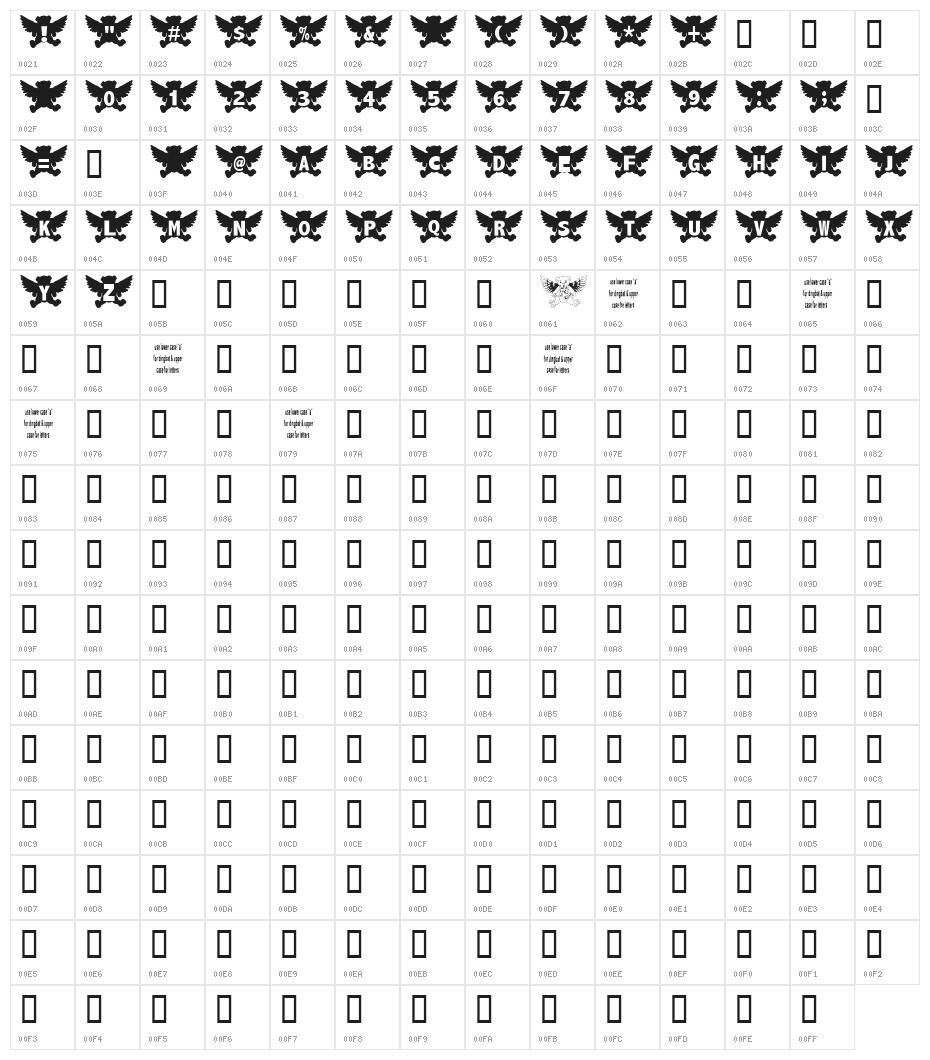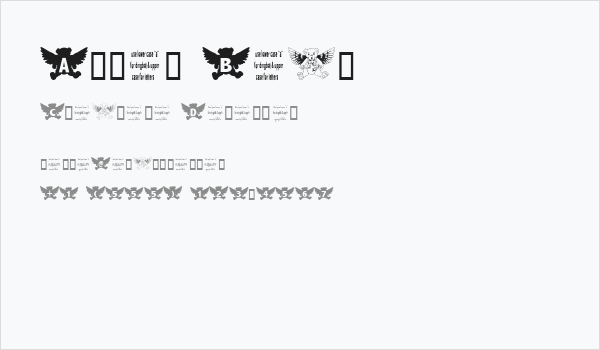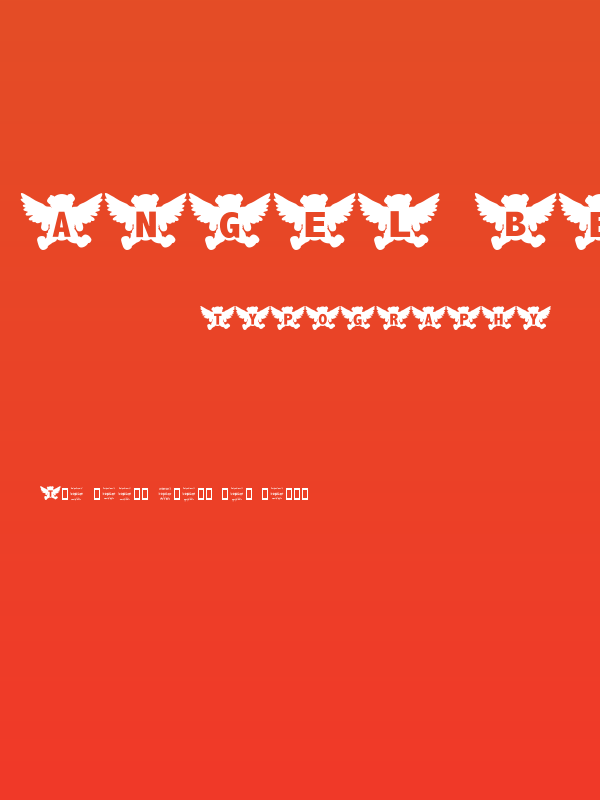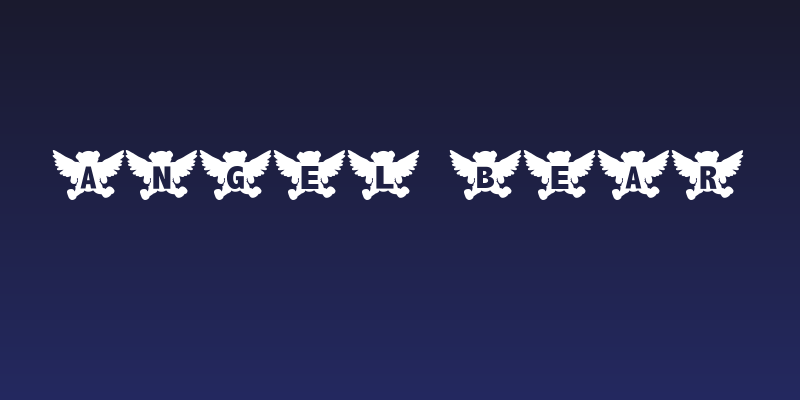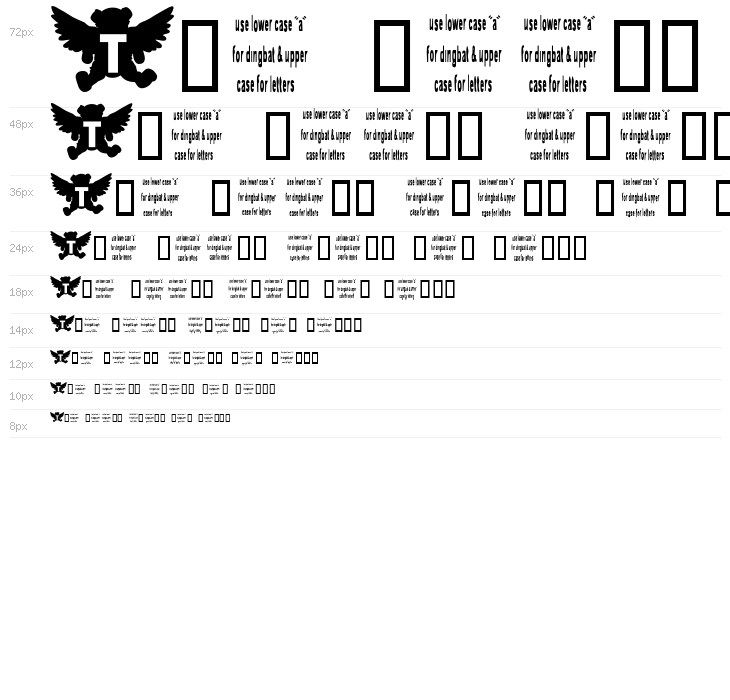
Angel Bear Font
| Caso de uso | Logos, Headlines, Posters |
| Proyectos propuestos | Ideal for children's book covers, playful event invitations, themed posters, or any project requiring a whimsical and decorative touch. |